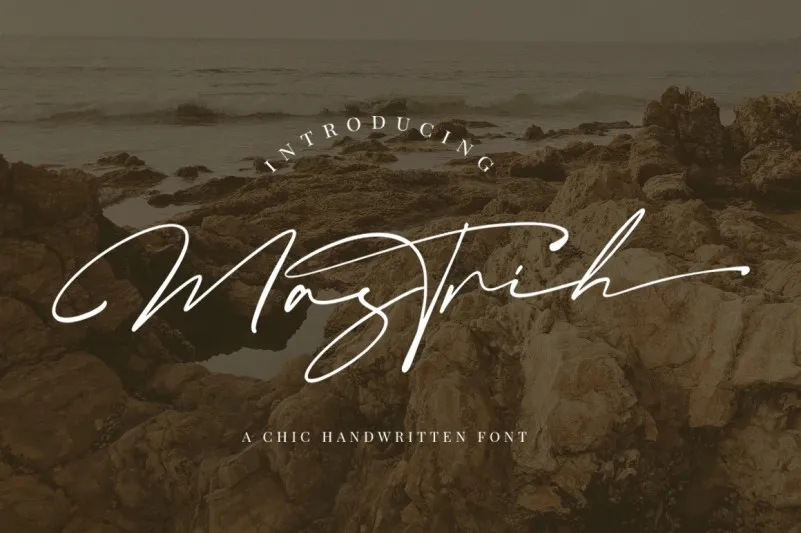
Mastrih Font é uma elegante fónta script criada para aqueles que valorizam a personalização única e os detalhes finos em seus projetos digitais. Inspirado nos encantadores traços de escrita do cotidiano moderno, essa fonte manuscrita rápida oferece um toque especial, perfeito para adicionar um toque único ao seu design. Ainda mais impressionante está a sua ligatura e variedade de estilos alternativos, que permitem dar vida aos seus projetos, tornando-os verdadeiramente únicos e floridos. Se você é um designer gráfico em busca de uma fonte moderna para seus trabalhos de texto ou criações digitais, Mastrih Font pode ser a solução perfeita. Inspirada nas sensações das mãos que escrevem com prazer, essa fónta oferece não apenas beleza formais, mas também a sensação quase autêntica de uma escrita real, tornando seus projetos mais vibrantes e vivos. Não hesite em experimentar Mastrih Font para adicionar um toque autêntico e encantador aos seus trabalhos digitais.